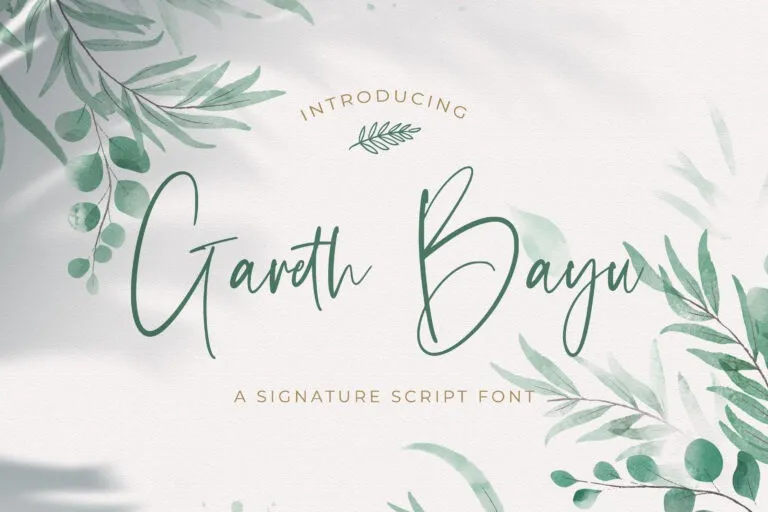
A Gareth Bayu Font é uma nova opção para designers que procuram um script moderno e elegante. Fabricada pela Stringlabs, essa fonte apresenta caracteres limpos e bem equilibrados, garantindo uma harmonia perfeita que complementa diversos projetos. Seja você criativo com ideias inovadoras ou simplesmente reutilize este design, perceberá como ela dá vida a seus trabalhos de arte digital. Aproveite esta fonte para dar um toque diferenciado aos seus projetos e revitalize suas criações com um estilo único e sofisticado.